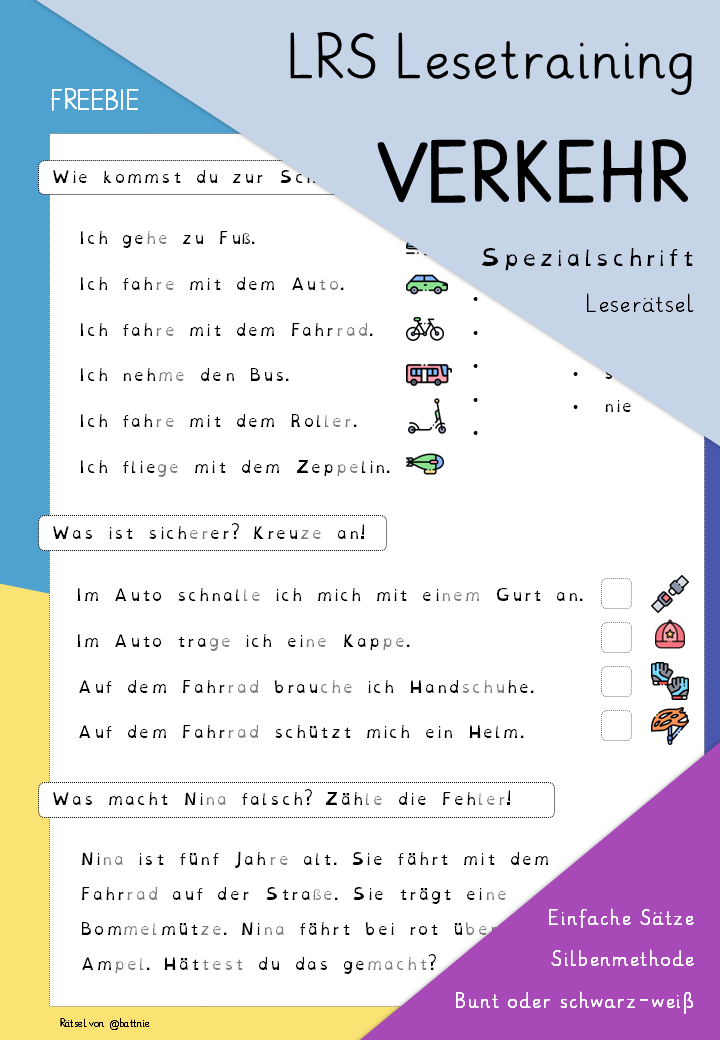
Lesetraining Verkehr
Dieses Material bietet spannende Lesetrainingseinheiten rund um das Thema Verkehr. Die Schüler*innen lernen spielerisch, verschiedene Verkehrsmittel zu erkennen und deren Sicherheit zu bewerten.
Spezialschrift
OpenDyslexic wurde entwickelt, um bei Symptomen von Legasthenie zu unterstützen: Die Buchstaben haben stark gewichtete Unterseiten, um die Textzeile zu verstärken und die Richtung anzuzeigen. Die einzigartigen Formen jedes Buchstabens und die größeren Abstände können helfen, Verwirrung durch Umdrehen und Vertauschen zu vermeiden.
LRS Training: Verkehr (Leserätsel, Open Dyslexic Font)